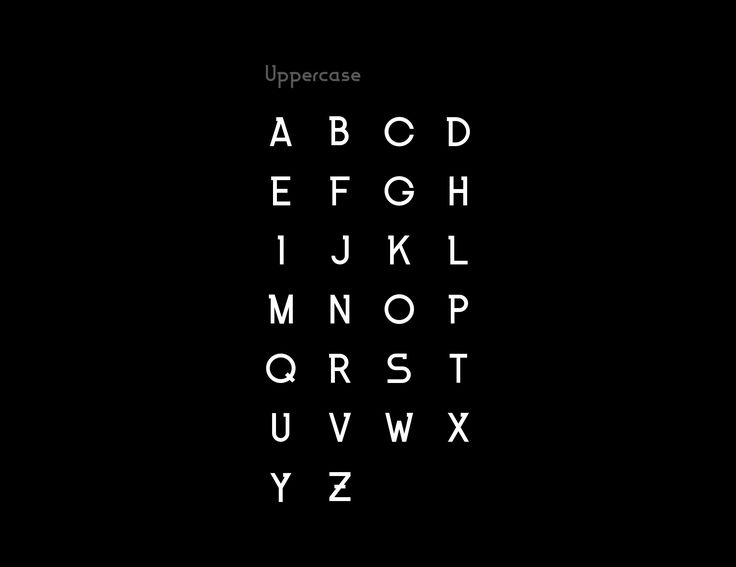
Pangram Sans
‘2800 тщательно обработанных глифов распределены по семи великолепным весам от ExtraLight до Black. Вдохновлен некоторыми из величайших геометрических шрифтов».
Coves